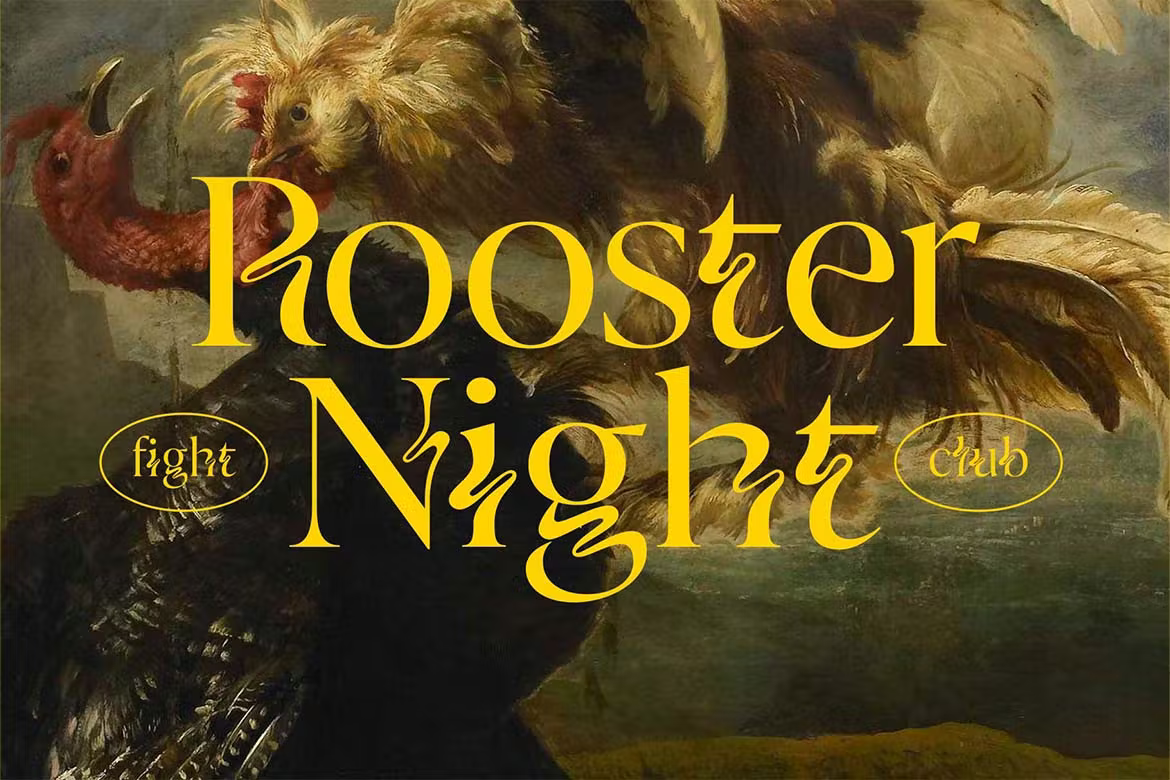
Zighead Display Font
Description de Zighead Display Font
Zighead Display Font est heureux de présenter une nouvelle police d’affichage, nommée Zighead. Cette police décorative comporte des caractères empattements forts et uniques qui coulent comme une rivière d’encre. Étant une combinaison de pointes acérées et de courbes douces, c’est intéressant mais ludique, offrant le piquant que vous recherchez. est une police majuscules et minuscules avec prise en charge de l’écriture latine standard, des chiffres et de la ponctuation. Cette police décorative se démarquera à coup sûr, avec ses glyphes uniques et hautement stylisés, parfaits pour absorber les mots-symboles et les affiches typographiques.
Prise en charge du langage d’écriture latin standard
Police majuscule et minuscule